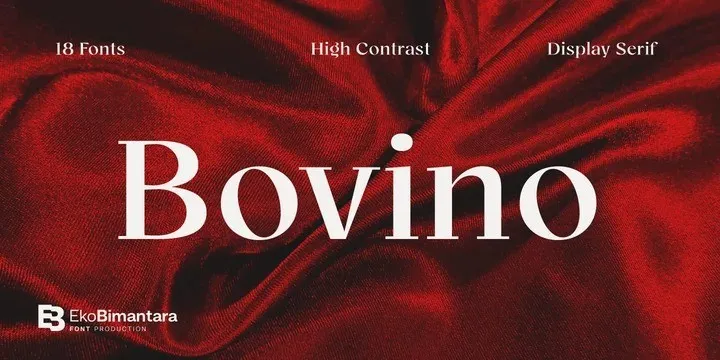
Bovino Trial Serif Font Family – Download Grátis
A Bovino Trial Serif é uma elegante fonte serif que oferece uma ampla gama de possibilidades. Construída pela fusão entre geometria e equilíbrio óptico, a fonte carrega um ar poderoso e pontiagudo, projetada pelo designer Eko Bimantara. Seu x-tamanho moderado e contra-estímulos altos tornam-a atrativa para títulos e usos de grande tamanho. A Bovino Trial Serif abrange mais de 400 gílios, cobrindo uma ampla variedade de idiomas românticos, incluindo uma gama completa de sete estilos, desde o fino até o preto, todas com seu respectivo itálico. Ideal para gráficos e projetos que buscam um contraponto elegante em seus designs.